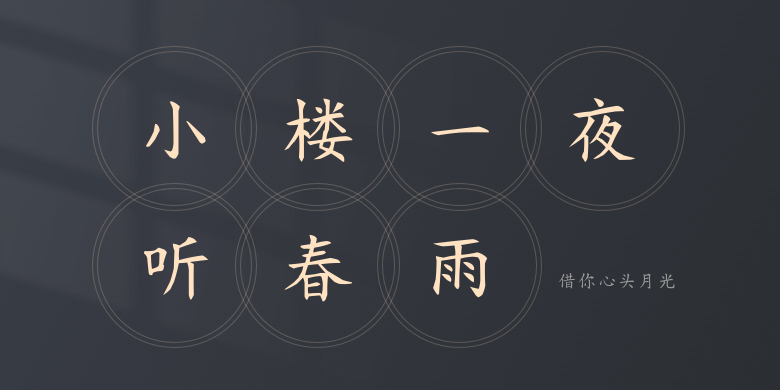
借你心头月光
借你心头月光,这款字体结构工整、笔画清晰,兼顾美观与易读性,适用于标题、正文、海报、包装、LOGO 等多种场景。字形优雅稳定,风格百搭耐看,适配日常排版与创意设计,让文字呈现更舒适、更具质感。借你心头月光一笔一画,皆是细节,以均衡的比例、流畅的线条打造舒适视觉体验,字形端正大气,风格简约现代。无论是商业设计、品牌宣传还是日常排版,都能轻松驾驭,让文字更有格调与力量。借你心头月光字体下载。